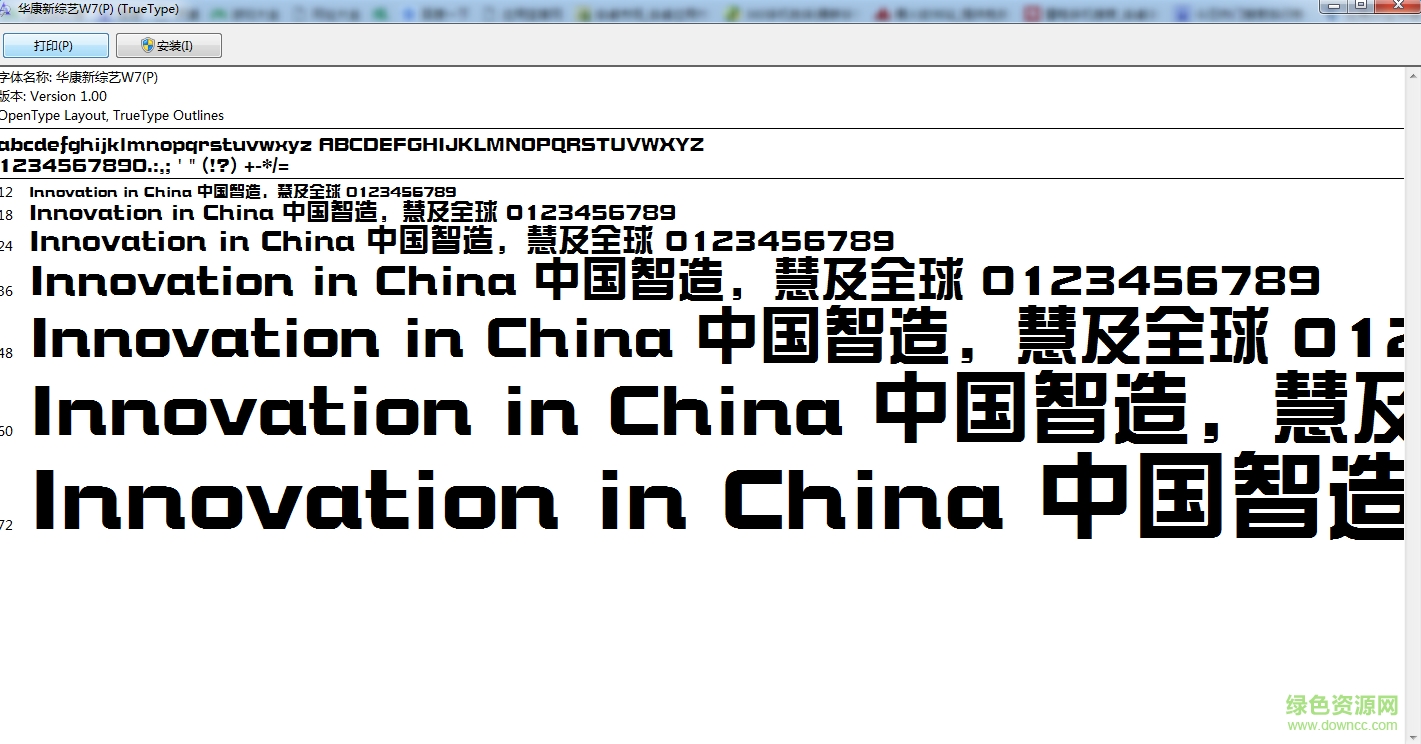
dfpzongyiw7字體是使用非常廣泛的一款字體,我們經(jīng)常能在影視作品開頭那些logo字體,還有廣告設計的大字體看到這個字體,這個字體使用非常的廣泛,而且字體也確實很漂亮,喜歡這個字體的用戶,快來綠色資源網(wǎng)下載吧!
dfpzongyiw7字體又叫華康新綜藝w7字體,字體飽滿,渾厚婉轉,用途廣泛,適用于策劃設計、包裝設計、廣告設計、影視影視等眾多領域。
dfpzongyiw7是一套常見及常用的POP廣告字體,以黑體為基本出發(fā)點,外觀更趨方正,外張,結構與筆劃更善于平均分布,擺脫了傳統(tǒng)黑體之規(guī)范,更具自由。